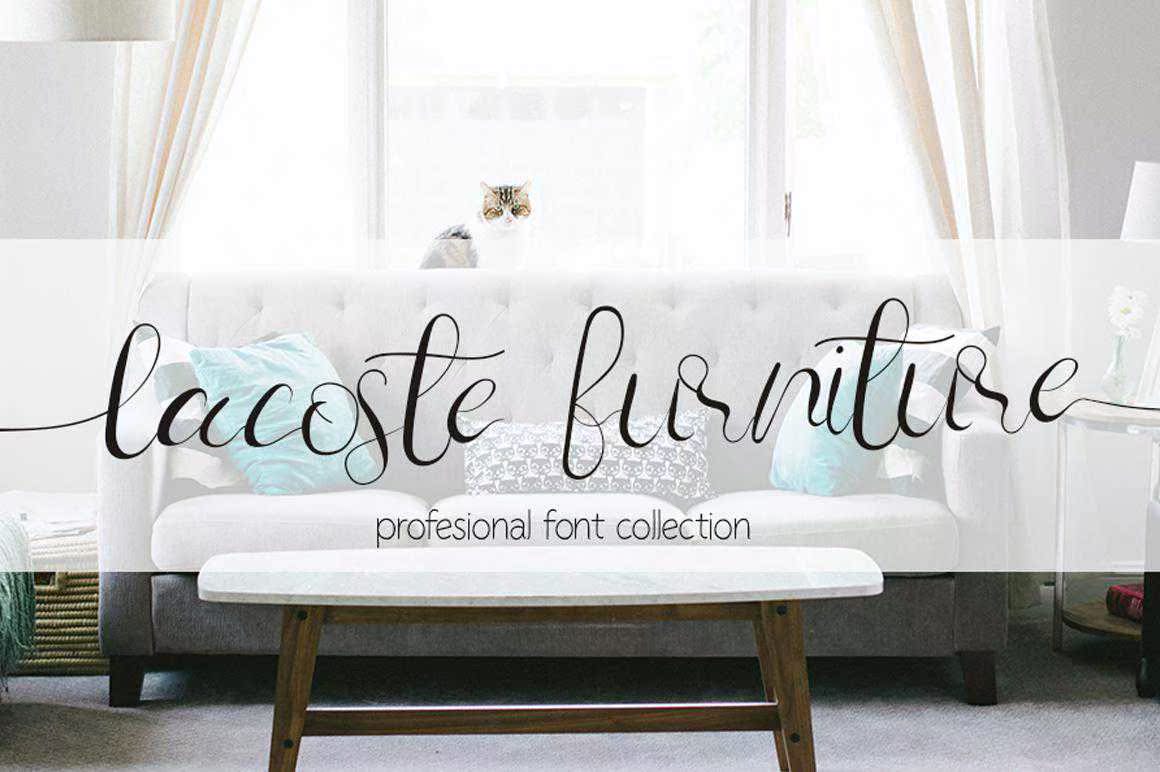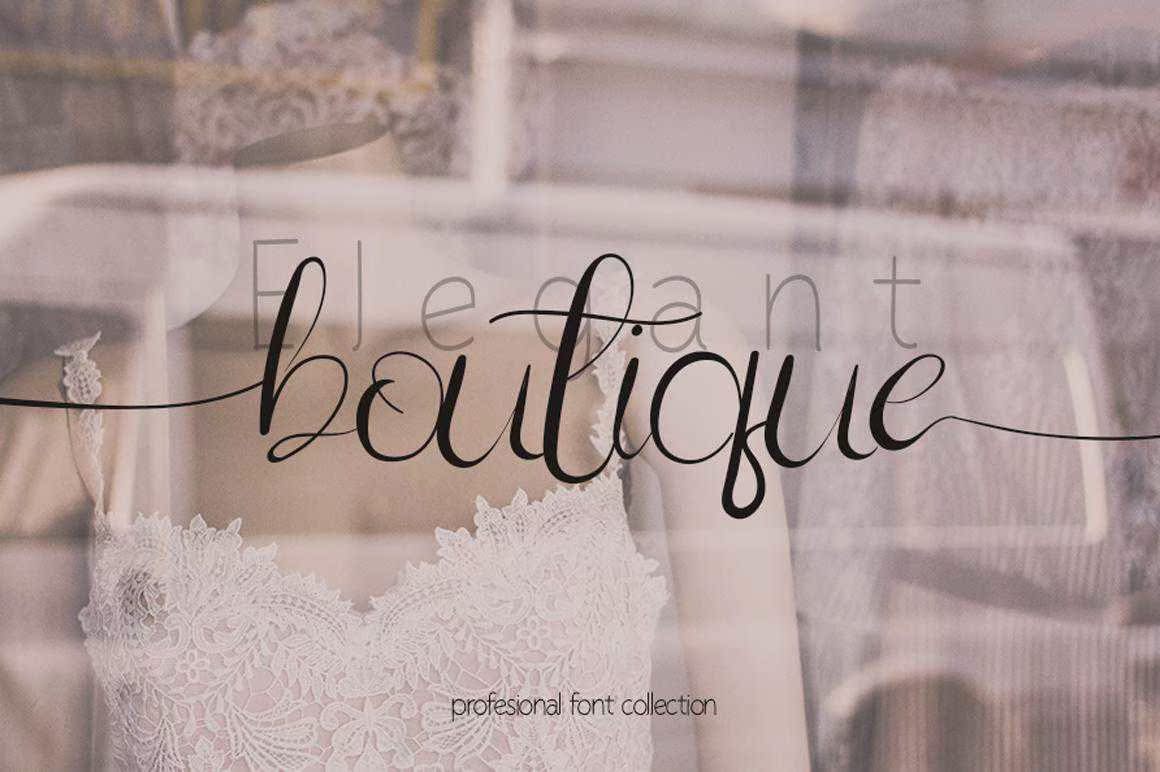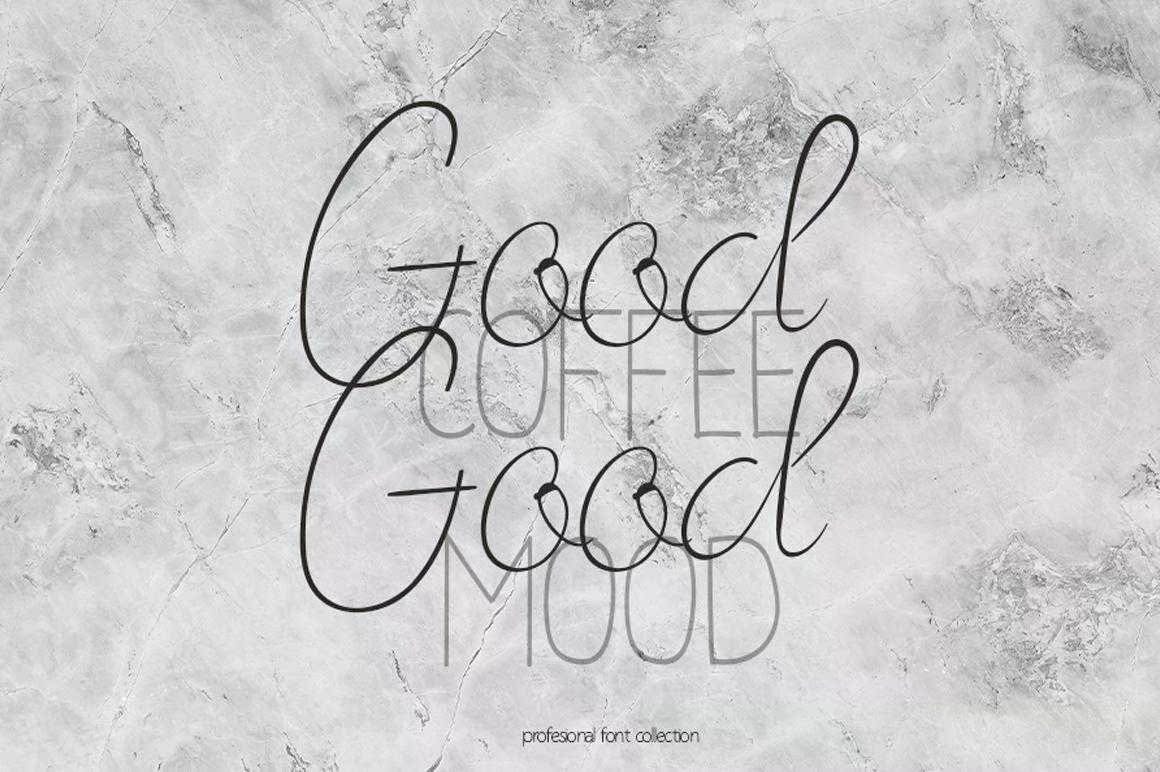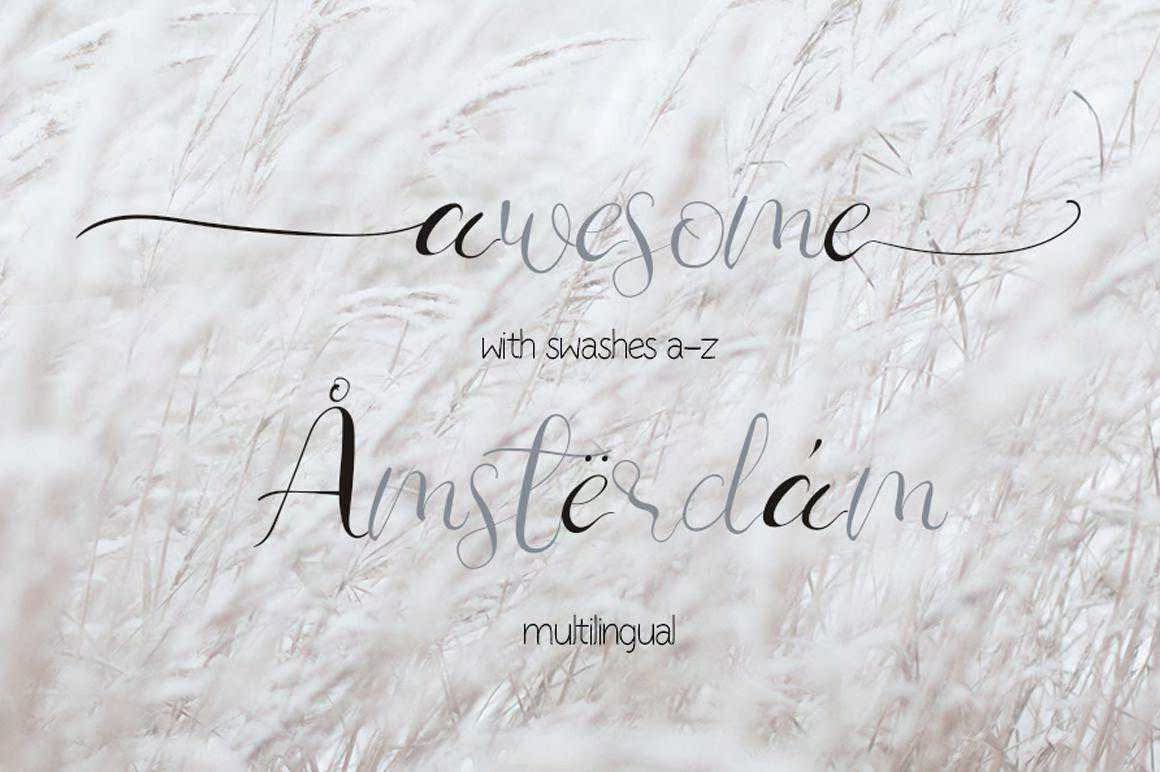
婚礼浪漫场景SaravishingScriptFont。此字体笔迹简洁且非常详细。无论是什么样的主题,此字体都将极好地保存到您的字体库中,因为它有可能增强任何创作。此字体编码意味着您可以访问所有字形和Swashese!婚礼浪漫场景SaravishingScriptFont。此字体笔迹简洁且非常详细。无论是什么样的主题,此字体都将极好地保存到您的字体库中,因为它有可能增强任何创作。此字体编码意味着您可以访问所有字形和Swashese!